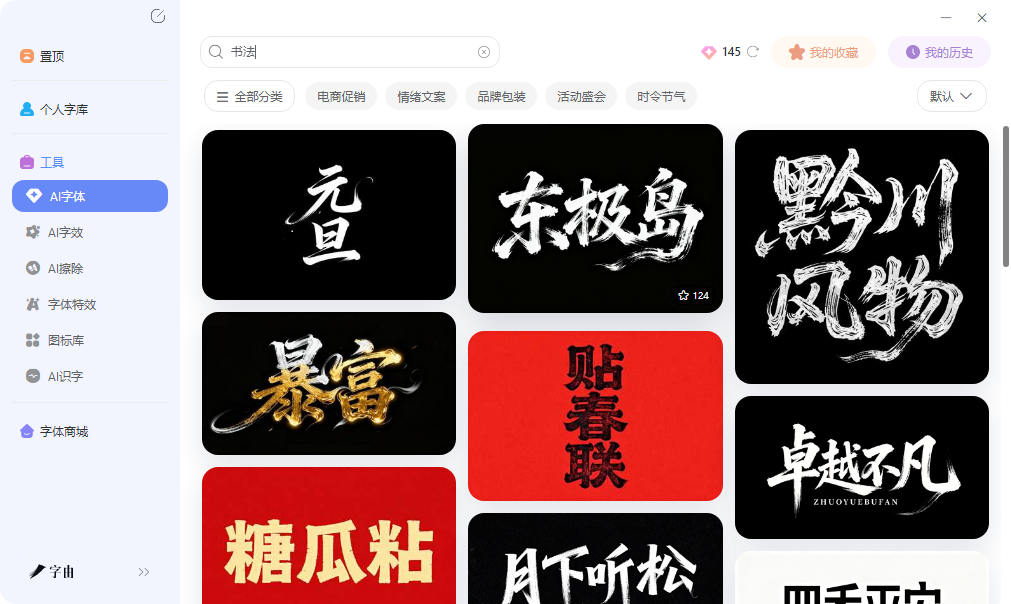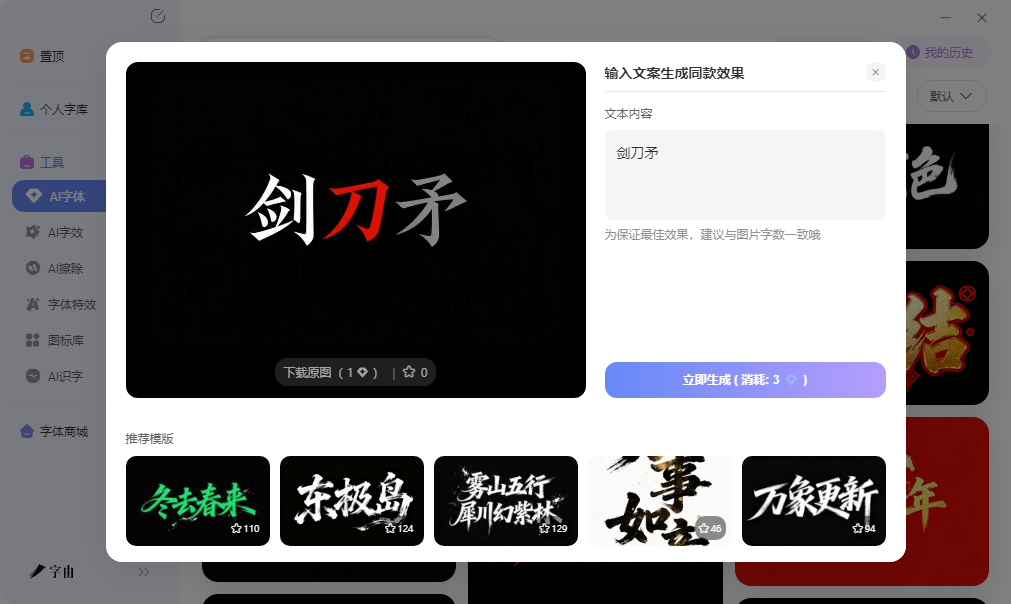
行书字体生成器在线转换,输入文字一键生成行书
想在海报标题、品牌Logo或个人签名中使用行书字体,但电脑自带的字体库里没有几款像样的行书体。网上下载的行书字体包经常缺字、变形,版权也不清晰。在线行书字体生成器可以解决这个问题:输入文字,选择行书样式,直接生成图片或复制文本。这篇文章测试了5款行书字体生成工具,分别介绍它们的操作方式、字体选项和输出格式。
字由AI字体模块专门设有书法一类的模板。这些模板不是简单的字体渲染,而是包含了完整的排版和特效处理。每个行书模板的字体已经选定,笔画的连笔处、轻重变化、起收笔形态都已调校到位。同时模板还预置了背景色、纹理、阴影或发光等特效,用户不需要额外配置。
你只需要打开字由客户端,点击顶部AI工具进入AI字体页面。在左侧风格标签列表中找到手写书法或国潮风分类,这两个分类中包含了行书风格的模板。用户也可以直接在搜索框输入行书或行楷,系统会筛选出所有相关模板。每个模板下方有一行示例文字,展示该模板的行书风格。用户将示例文字删除,输入自己的文案,点击生成按钮。系统在10到20秒内生成一张PNG图片。图片尺寸适合网页和印刷使用,背景默认为透明。
生成结果的特点:不同于普通字体转换器输出纯文本,AI字体生成的是完整图片。这意味着行书的笔触粗细变化、飞白效果、墨迹浓淡都能保留下来。同时图片自带排版,文字的字间距、行距已经确定,用户拿到后可以直接贴到海报或封面中。如果用户需要调整排版,也可以在生成后手动裁剪或缩放图片,但不能修改文字内容本身。
第二个网站是猫眼艺术字。它的行书字体板块提供了方正硬笔行书简体、陈继世硬笔行书、经典行书篇、钟齐陈伟勋硬笔行书、钟齐立强行书简、李旭科毛笔行书、茹新诗行、简细行楷、蔡云汉行书、德虎行书、安景匡行书、书体坊破笺等多款行书字体选项。用户输入文字后,可以从下拉菜单中任选一款行书字体,页面实时预览效果。页面下方还提供了字体预览快速切换区域,用户可以点击方正硬笔、继世硬笔、经典行书等快捷入口,快速切换字体样式。这个工具适合需要快速对比多款行书字体效果、或者需要在行书文字上加投影、旋转、渐变等简单特效的用户。
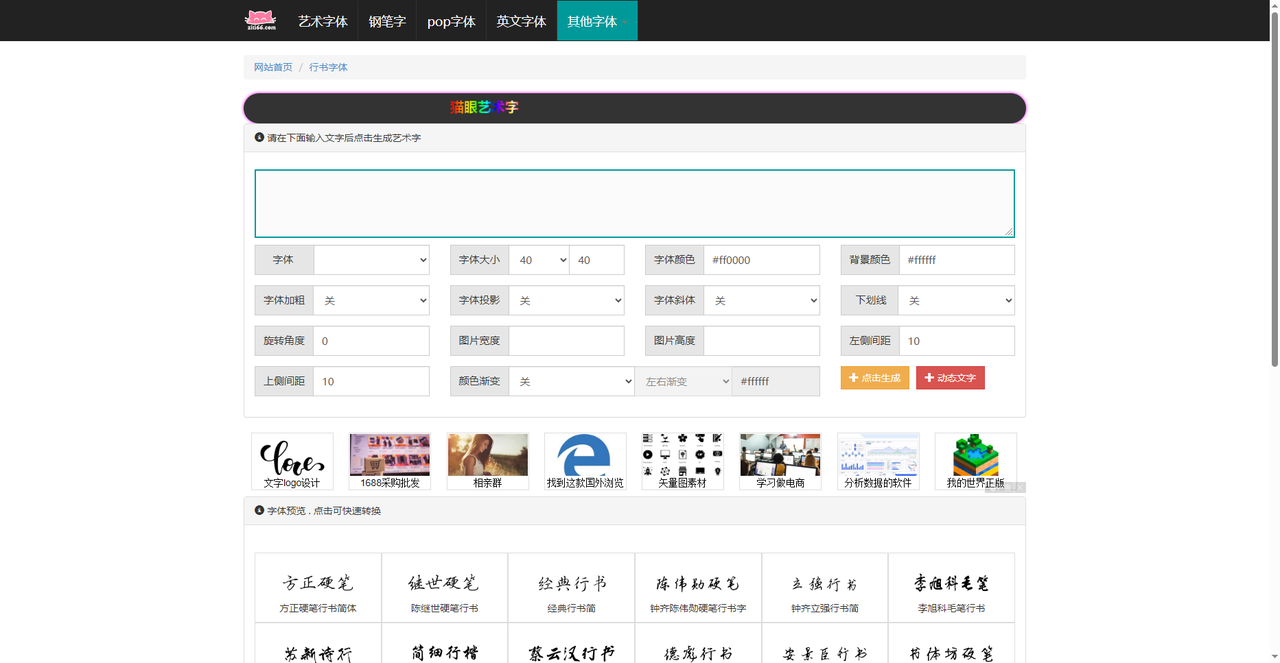
第三个网站是一个专门的书法字体生成器,支持书体坊硬笔行书、叶根友毛笔行书简体、叶根友刀锋黑草、叶根友书法等字体选项。用户输入文字后,从下拉菜单或快捷入口中选择一种行书字体。用户可以将鼠标悬停在图片上右键保存,或在手机上长按保存。这个工具还预设了其他书法字体快捷入口,包括向佳红字迹、中华金榜体、宋徽宗瘦金体等,方便用户在同一页面切换不同书法风格。
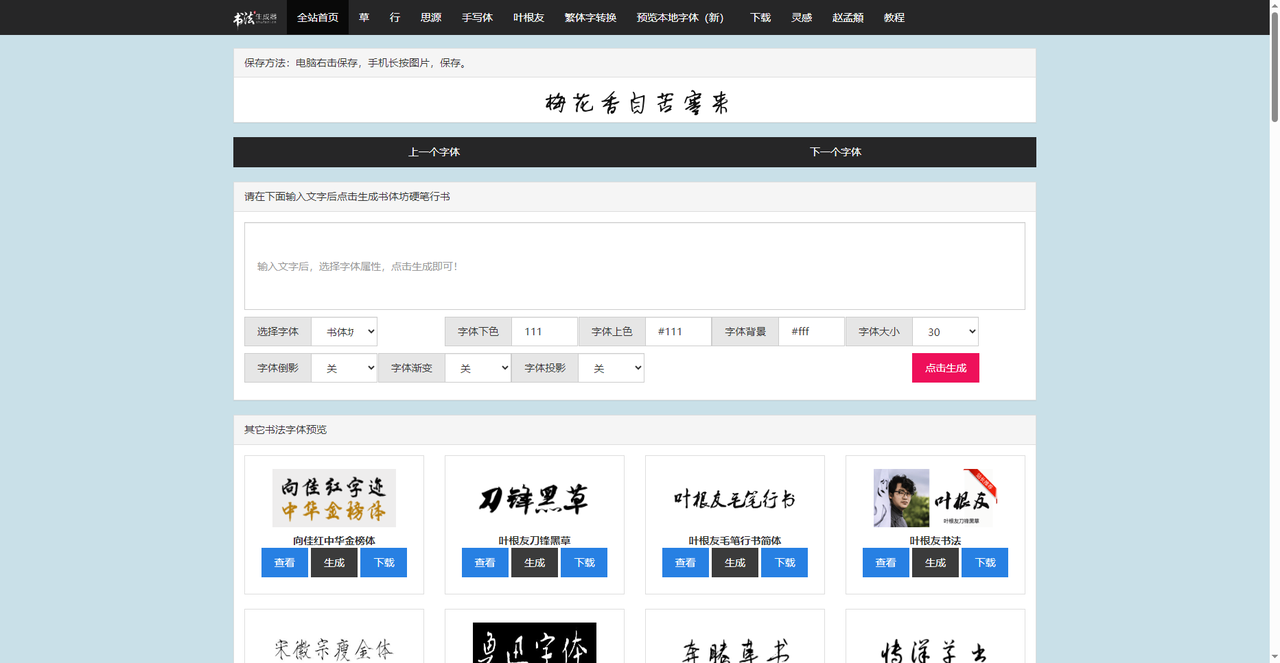
第四个网站是字体家。它是一个中文字体平台,集成了字体下载、AI造字、字体转换器等功能。在字体标签列表中,专门设有行书字体在线转换这一分类。用户点击行书字体在线转换标签后,系统会展示支持行书转换的字体列表,例如叶根友刀锋黑草等。用户输入文字,选择字体,可设置大小、背景,还可以添加抖音风格、空心字、阴影、线性渐变、径向渐变、3D效果等特效。点击在线转换按钮后生成图片。
字体家的优势在于它将行书字体转换与其他字体处理工具整合在一起,用户可以在同一个平台完成从选字、转换到特效添加的全部操作。对于需要制作行书风格电商主图、社交媒体封面图且有特效需求的用户,这个工具可以减少在不同平台之间切换的时间。页面也提供了字体详情和商用授权入口,方便用户确认字体版权后购买。
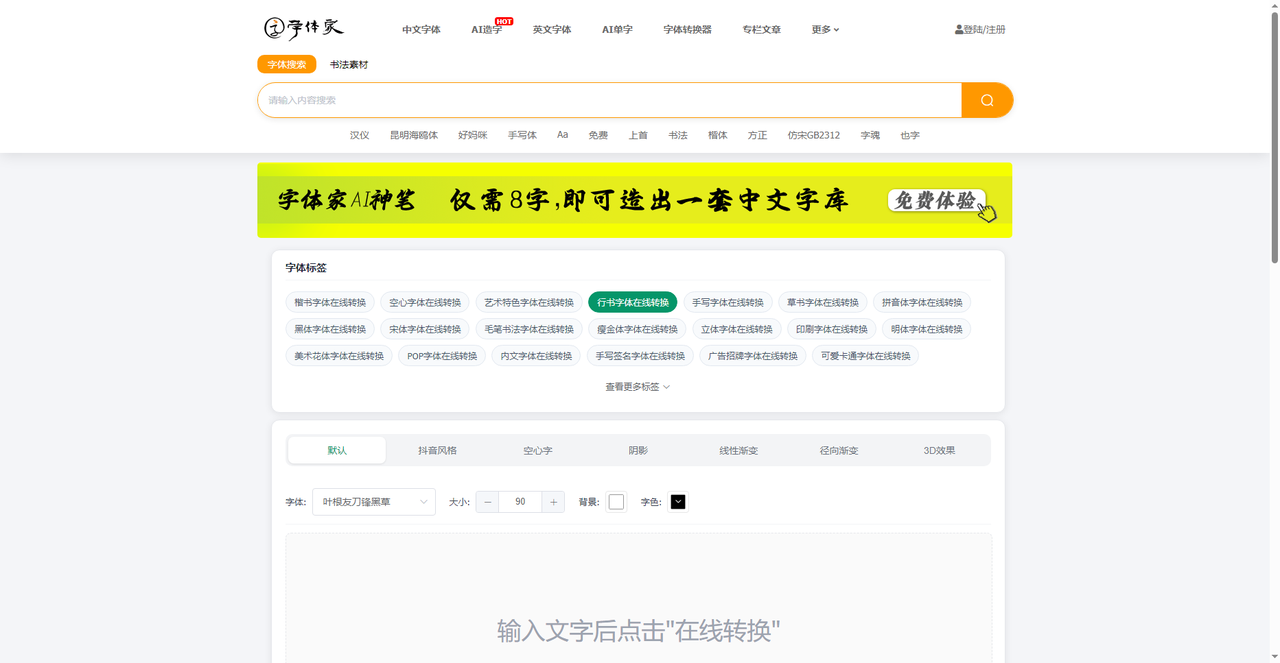
第五个网站是第一字体网。它在字体转换器板块中专门设有行书字体转换器,提供司马彦行书、奶酪字体、手写字体、毛笔字等多种转换选项。司马彦行书是较为知名的硬笔行书字体,笔画规整流畅,适合用于正文排版或日常文档标题。
用户在上方输入文字后,从下拉菜单中选择司马彦行书或其它行书选项,调节字号(默认80px)、行高(默认120px)、字体色、背景色(支持透明),点击生成图片按钮即可预览。转换结果下方标注了个人非商用免费、个人商用付费、企业商用付费三种授权方式。用户可以根据自己的使用场景选择对应的授权类型,避免商用侵权。